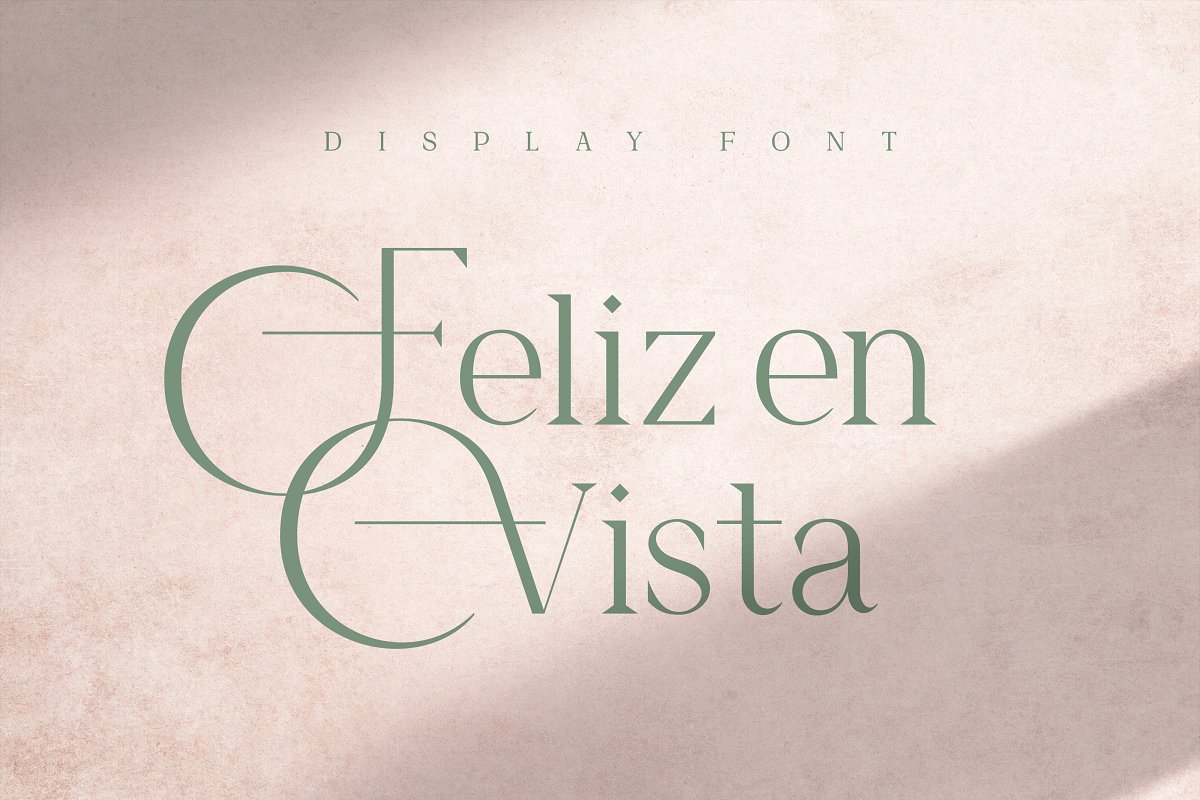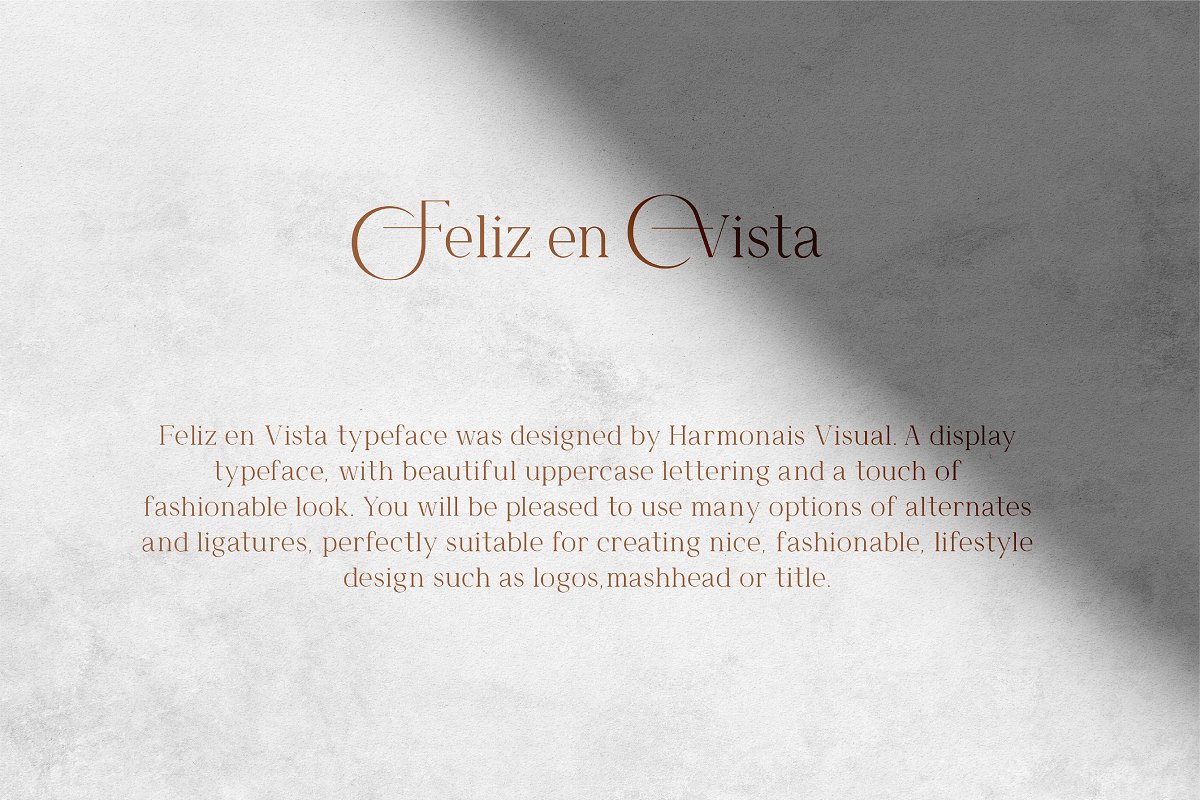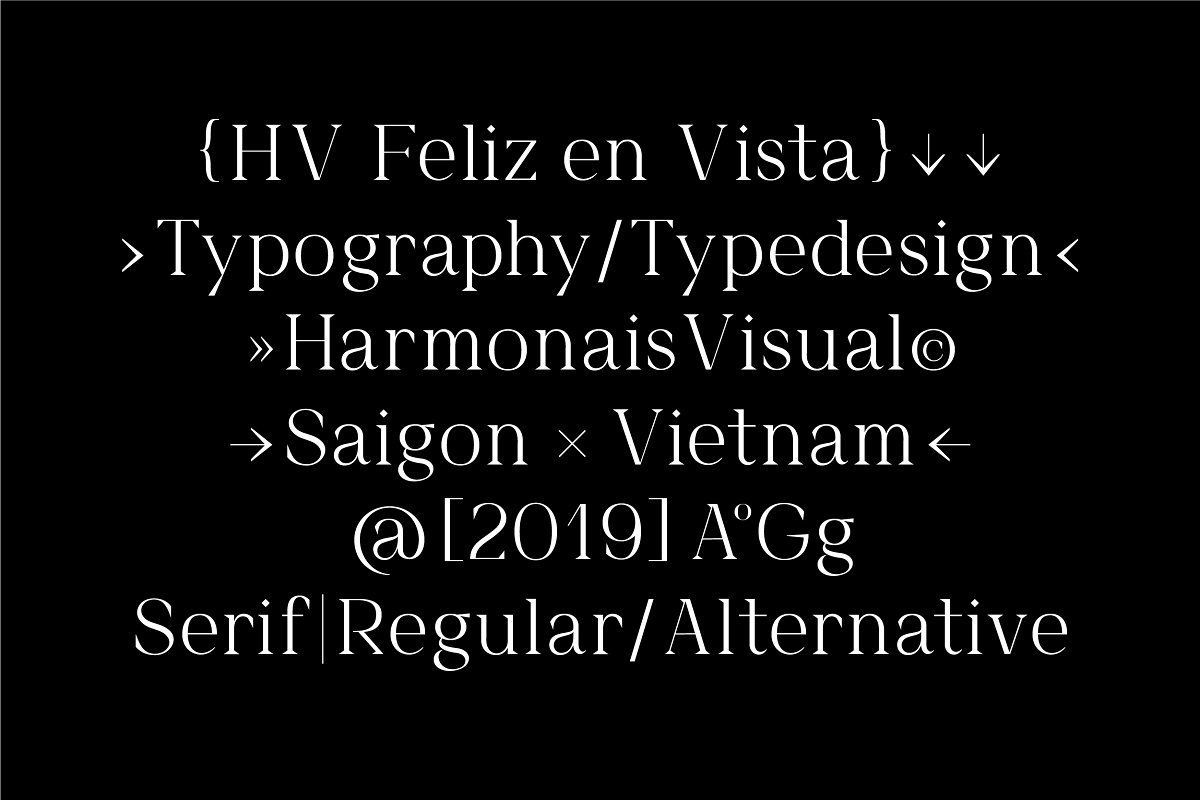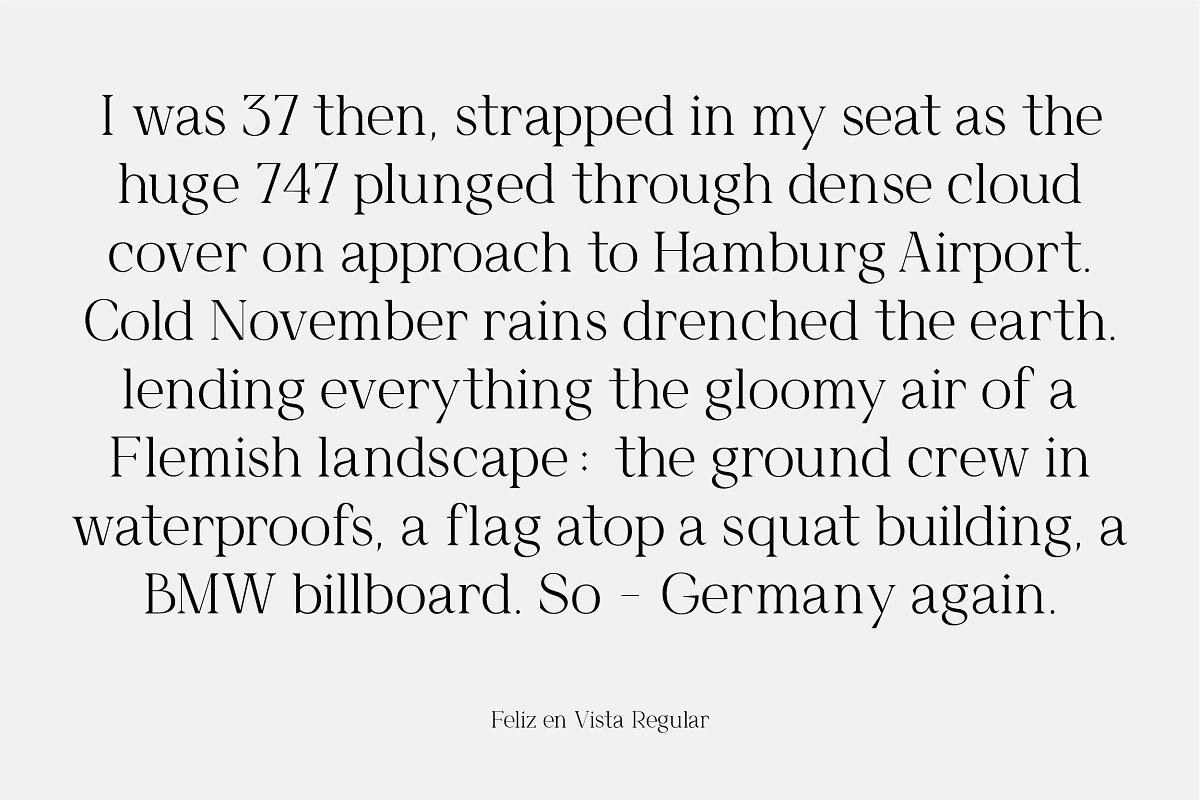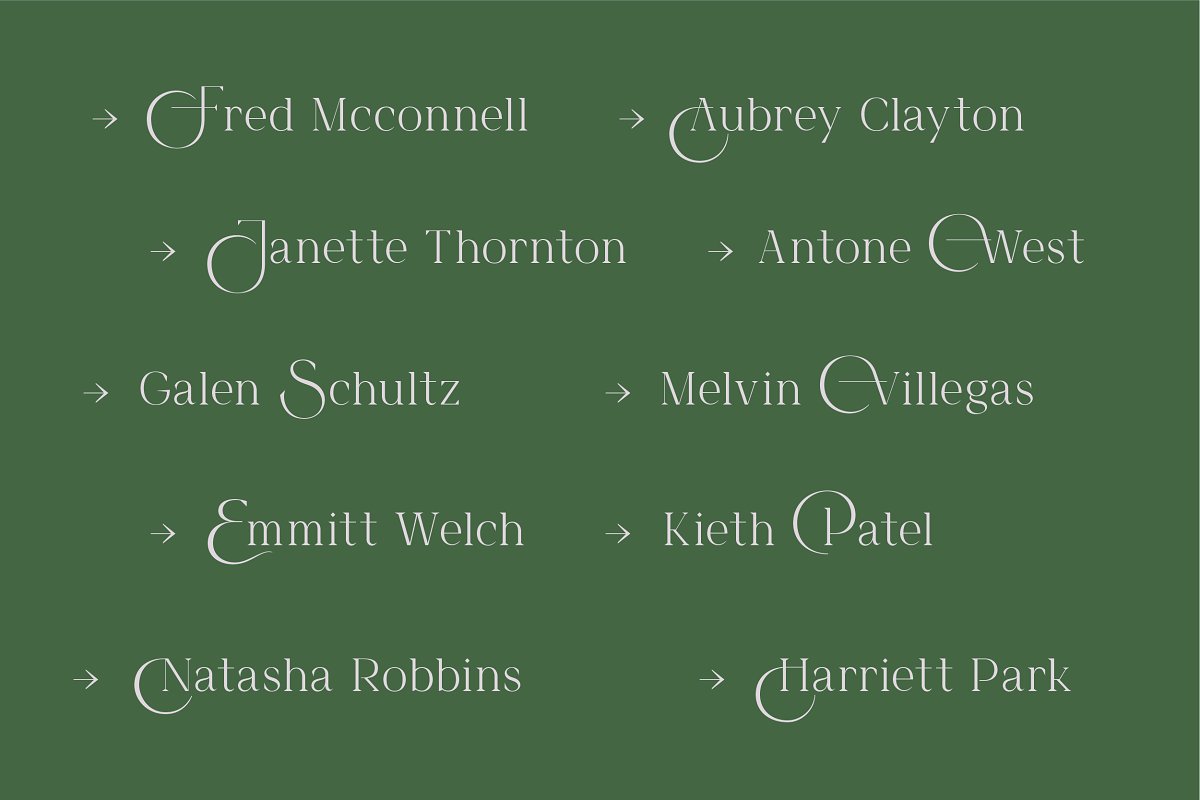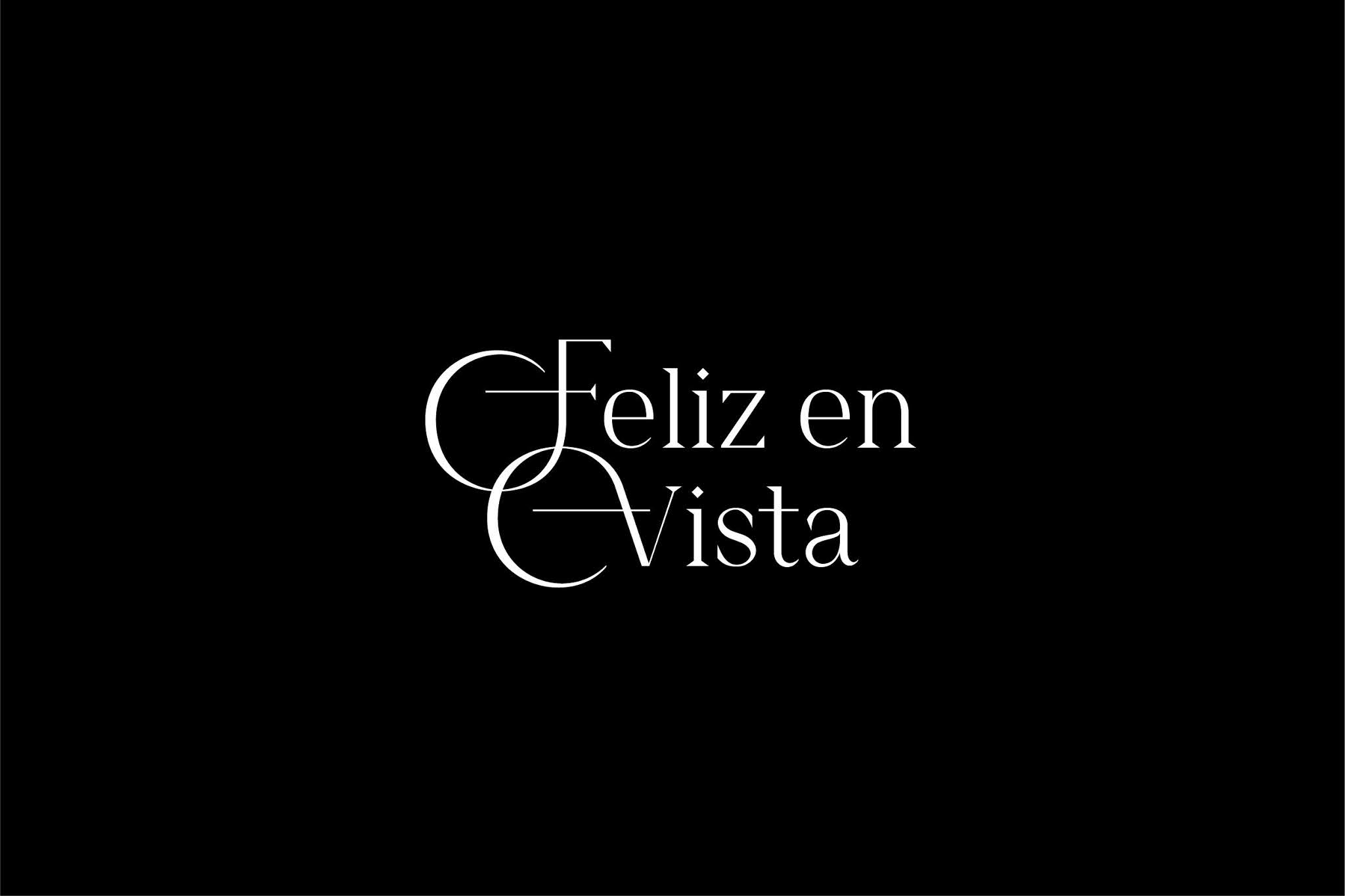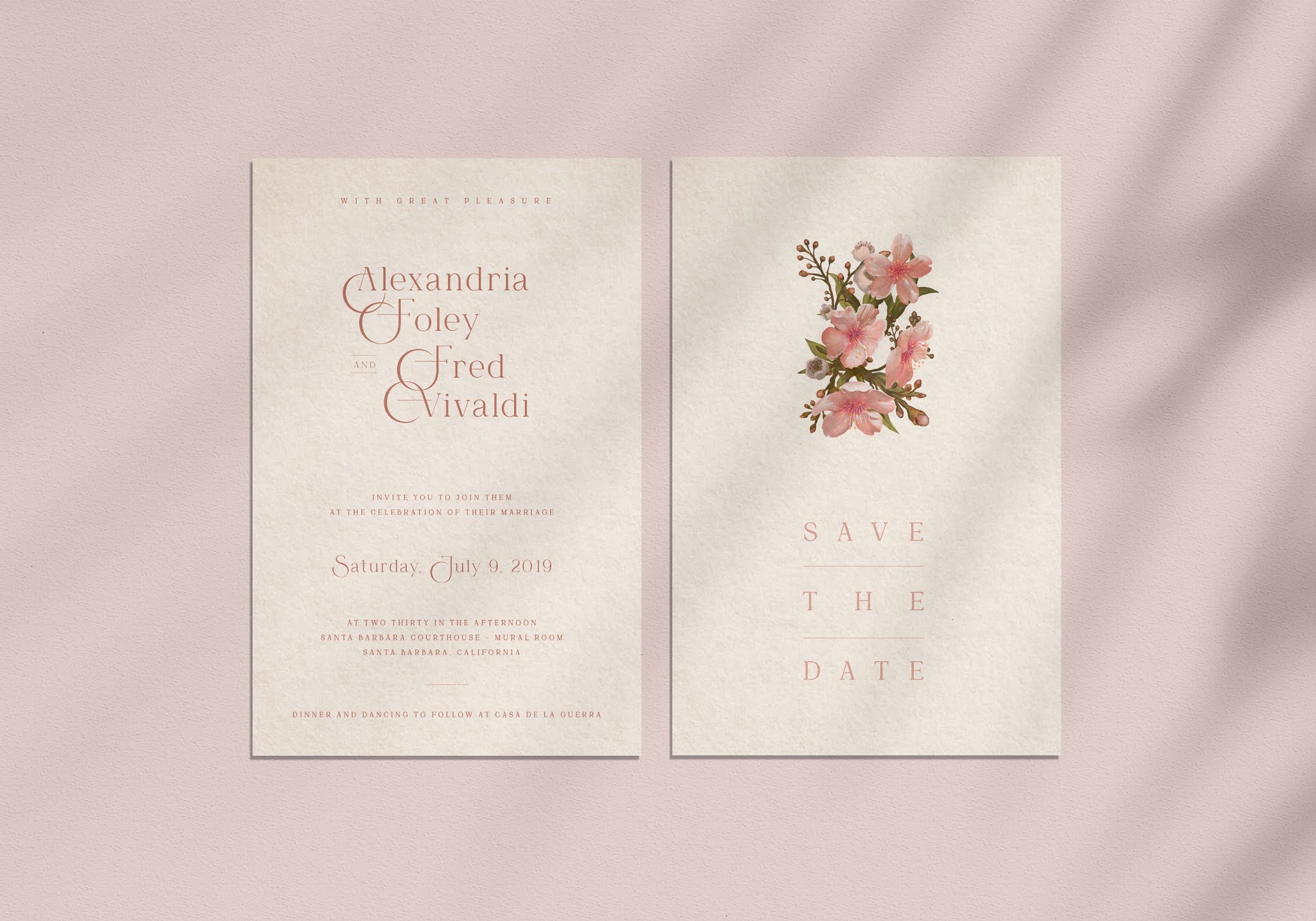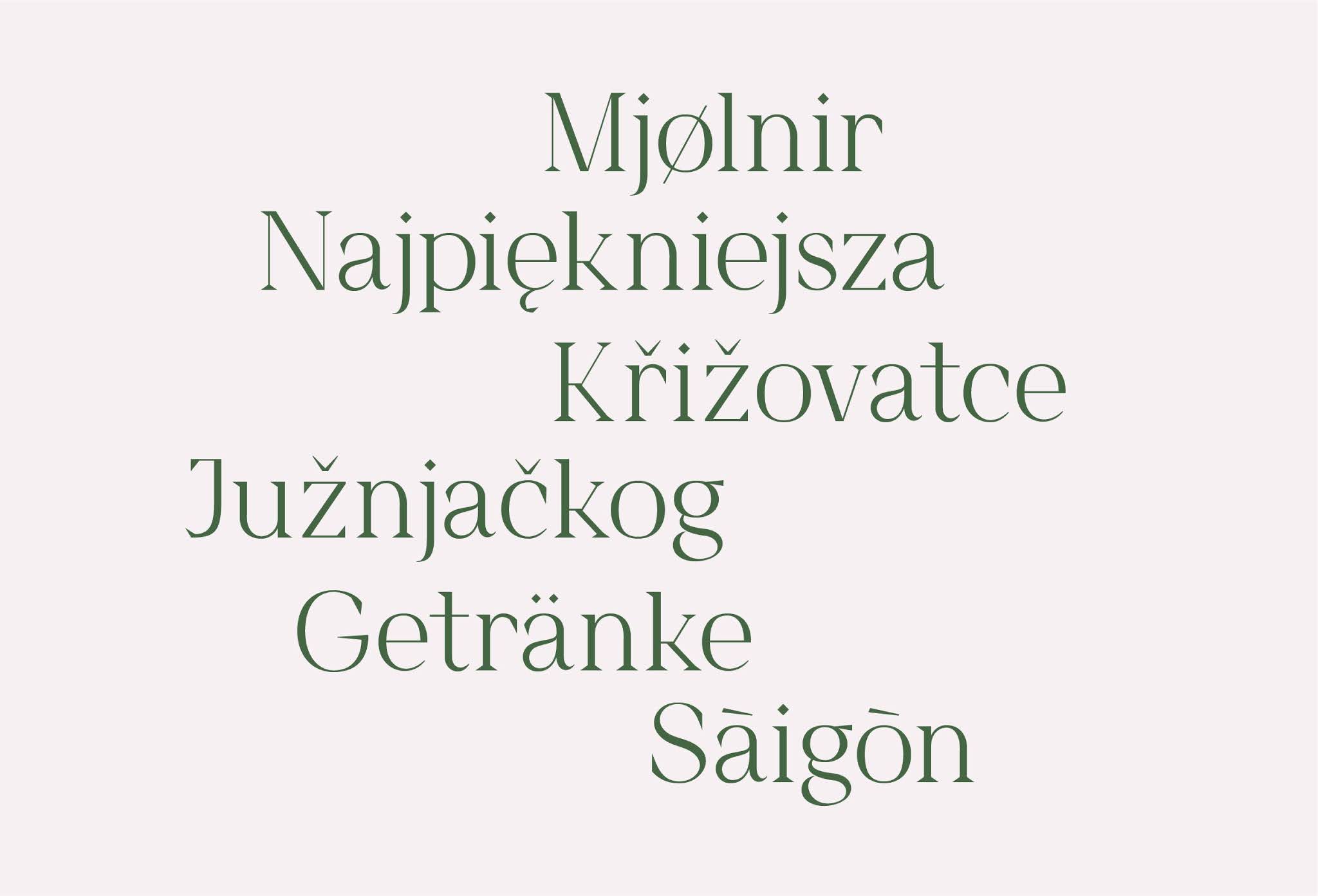
Feliz en Vista – một sefif hiện đại, kiểu chữ hiển thị với chữ in hoa đẹp mắt và một chút giao diện thời trang. Bạn sẽ hài lòng khi sử dụng nhiều tùy chọn alternate và ligature, hoàn toàn phù hợp để tạo thiết kế đẹp, thời trang, logo, mashhead, tiêu đề và thiệp cưới.
Đặc biệt font Feliz en Vista này gõ được Tiếng Việt nhé các bạn.